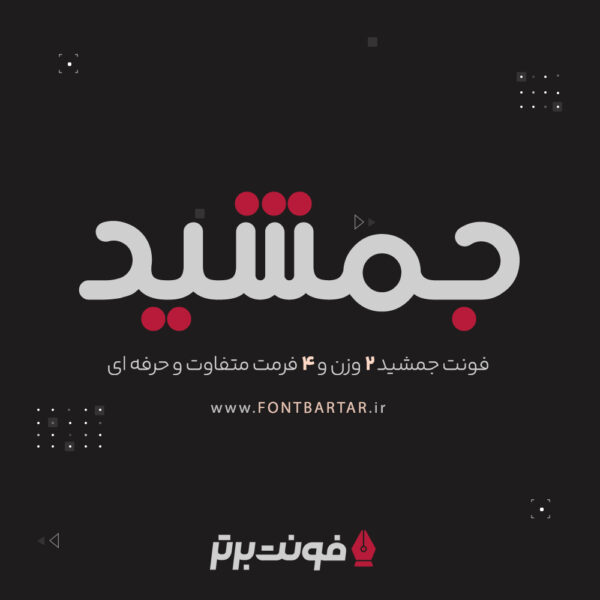
فونت فارسی جمشید
Jamshid Font
فونت فارسی جمشید با استفاده از دوایر و زوایای زیبای ریاضی طراحی شده است. در طراحی این فونت سعی شده تا اندازه کافی همه چیز متناسب باشد. نظم کلی حاکم بر فونت بر زیبایی این فونت اضافه می کند. در طراحی این فونت سعی شده سایزها به خوبی نمایش داده شود، شما می توانید به کمک فونت جمشید لوگوتایپ ، تایپوگرافی و طراحی های زیبایی را انجام دهید.
فونت جمشید دارای چند وزن است؟
• فونت فارسی جمشید در دو وزن معمولی و بولد می باشد.
فونت جمشید از چه زبان هایی پشتیبانی می کند؟
• از زبان فارسی و انگلیسی به همراه اعداد و علائم پشتیبانی می کند.
فونت فارسی جمشید